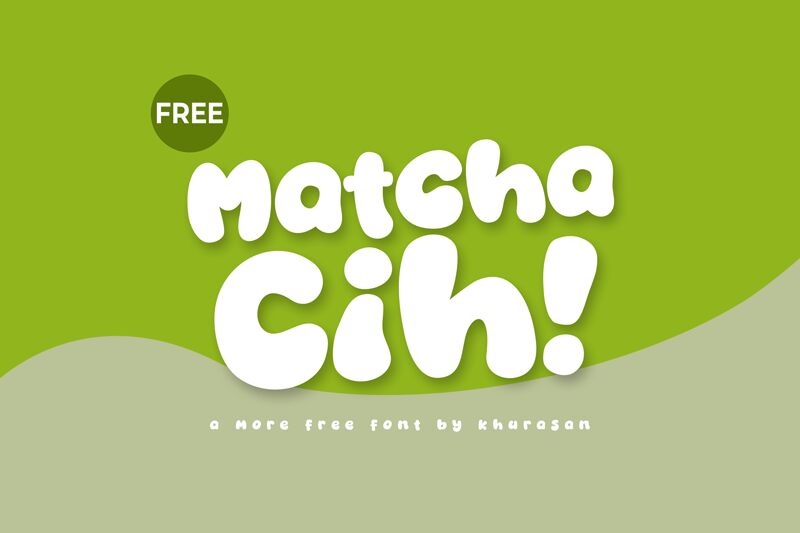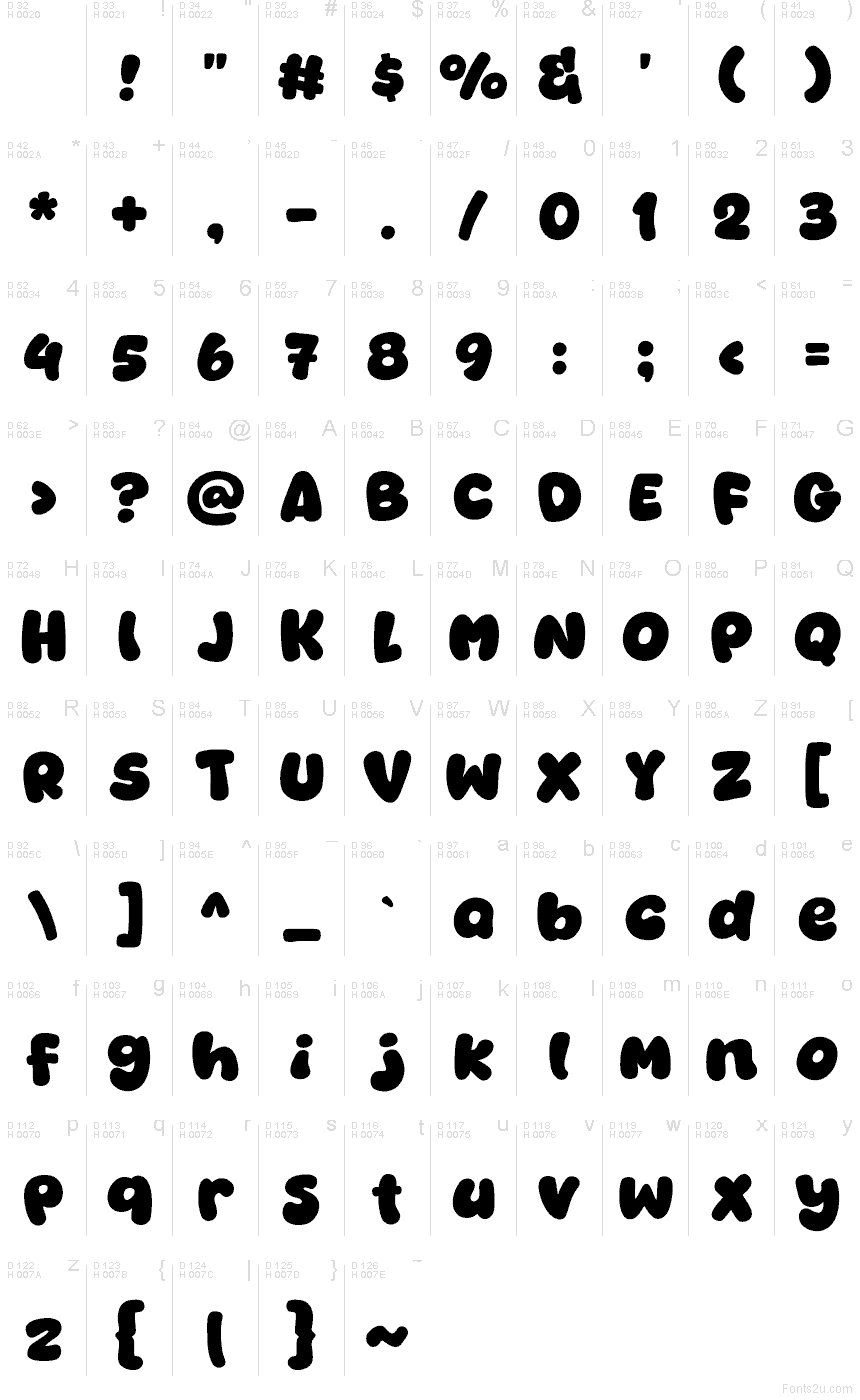
Matcha Cih par Khurasan est une police display de style cartoon gratuite, composée de grandes lettres gonflées qui semblent douces et ludiques au premier coup d'œil. Ses formes arrondies, ses raccords pincés et son rythme légèrement irrégulier lui donnent ce rebond propre au dessin à la main ; elle se lit presque davantage comme un personnage joyeux que comme un simple assemblage de caractères.
Cela en fait un choix tout naturel pour l'emballage de snacks, les couvertures de livres pour enfants, l'identité visuelle de cafés, la création d'autocollants ou les titres sur les réseaux sociaux, là où une tonalité amicale prime sur la formalité. En tant que police gratuite, elle est particulièrement efficace pour les titres courts et les logos, car ses courbes généreuses apportent chaleur et animation, même aux textes les plus brefs.